Cześć.
Uff, co to było za lato. Gorące i słoneczne. Całe lato spędziłam u nas nad Bałtykiem, w tym dwa tygodnie na pięknej wyspie Fehmarn, gdzie w tym roku nauczyłam się windsurfingu. Lato to dla mnie zawsze ten czas, gdy nie mogę usiedzieć w domu i ciągnie mnie czy to na plażę, czy na stand-up paddling. Końcówka lata była już chłodniejsza i – jak to bywa – musiałam trochę poletteringować, a przy okazji narysować wspomnienia w moim travel journalu. Ten wpis powstaje bardziej dla mnie samej, aby za rok sobie poczytać, co tam się u mnie działo i co rysowałam:)
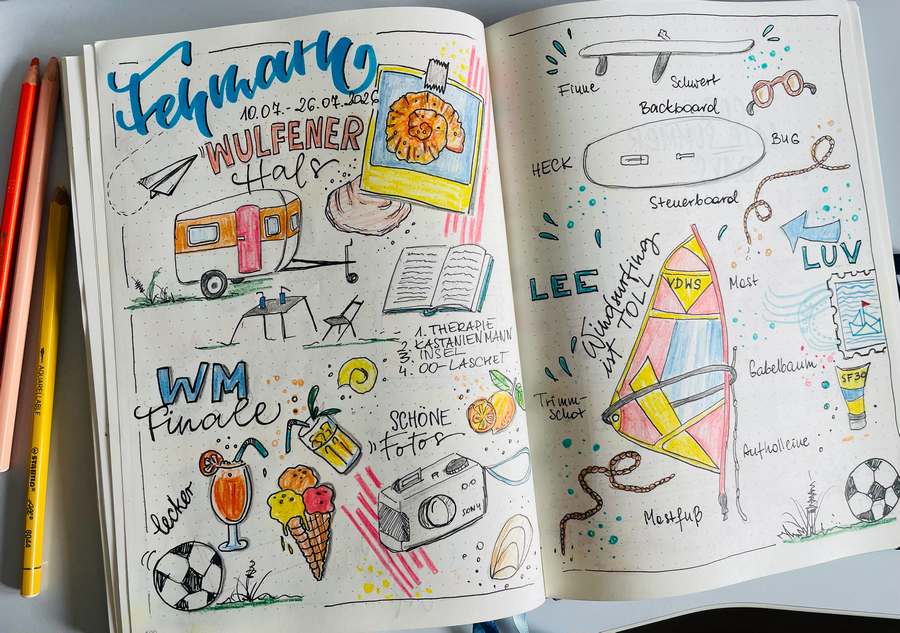
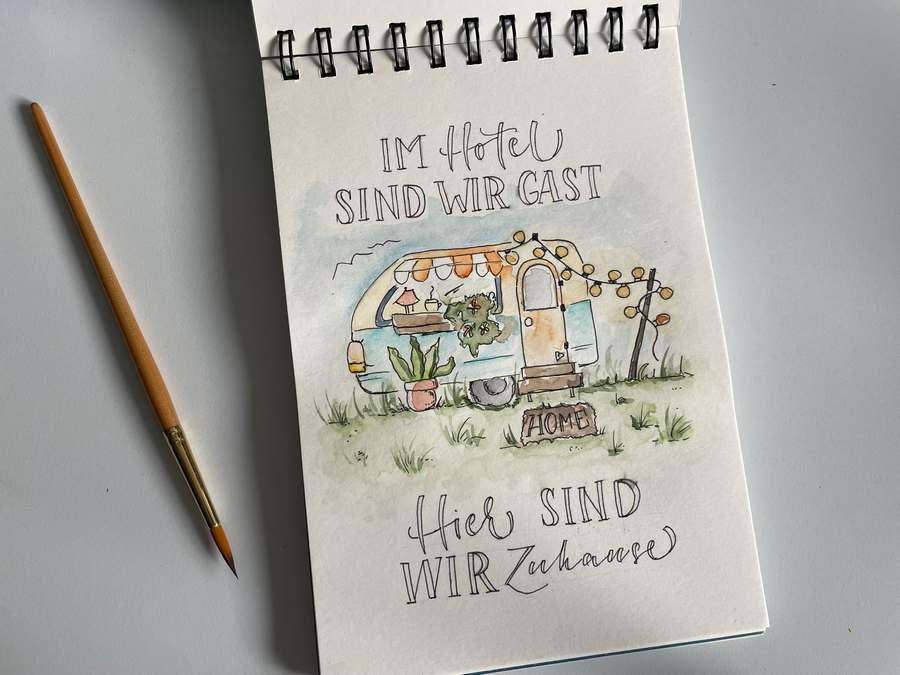
Niby nic nie wrzcuałam na IG, ale przeglądając swoje wakacyjne zdjęcia widzę, że kilka tych letteringów jednak było- czy to zwykłym ołówkiem, czy w Procreate. Ot, to moje ogormne hobby, które mnie bardzo relaksuje i tworzę sobie zwsze gdy nadejdzie mnie ochota.
W te wakacje przeczytałam i przesłucham (ja na mnie) sporą liczbę książek. Wszystkie były po niemiecku, więc niestety nic nie będę polecać 😀 Uwielbiam thrillery i kryminały, ale na liście znalazły się też komedia i romansidło- też fajne i wciągające. Musiałam się trochę zmusić do czytania i siedzieć na tyłku, a nie ciągle gdzieś latać- ja latem nie potrafię usiedzieć na miejscu- zwłaszcza, gdy jest piękna pogoda. W tym roku opaliłam się na maxa. W moim całym życiu nie byłam jeszcze NIGDY tak opalona. Praktycznie od końca maja mieliśmy pogodę i popołudnia spędzałam na plaży lub w ogrodzie. Kocham słońce i lato tutaj nad Bałtykiem….
Zdjęcia z tegorocznego lata- Bałtyk wyspa Fehmarn oraz u nas w Kiel-Schilksee 🙂 Ładnie u nas, prawda?
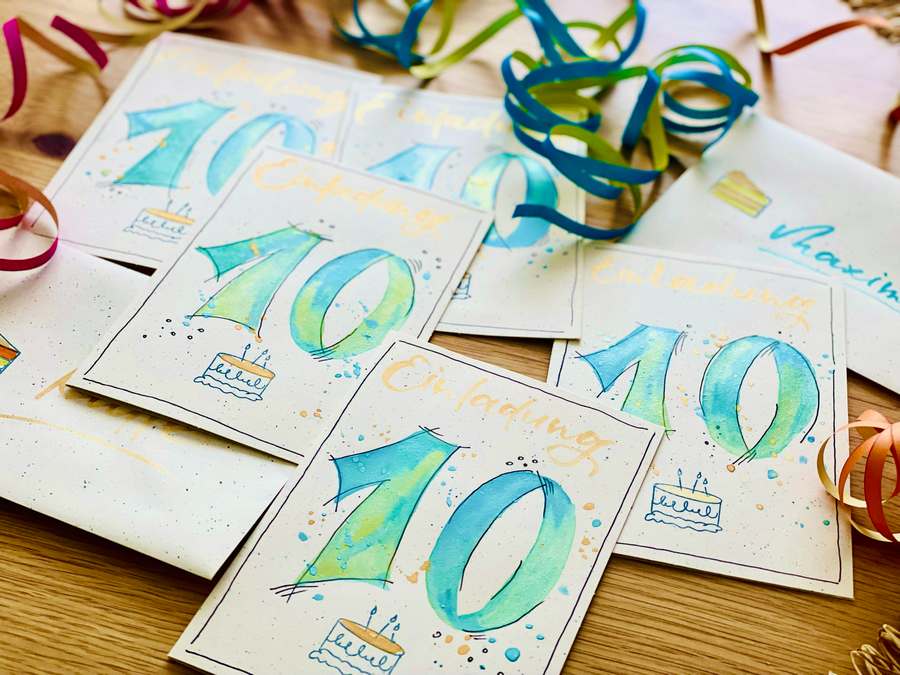
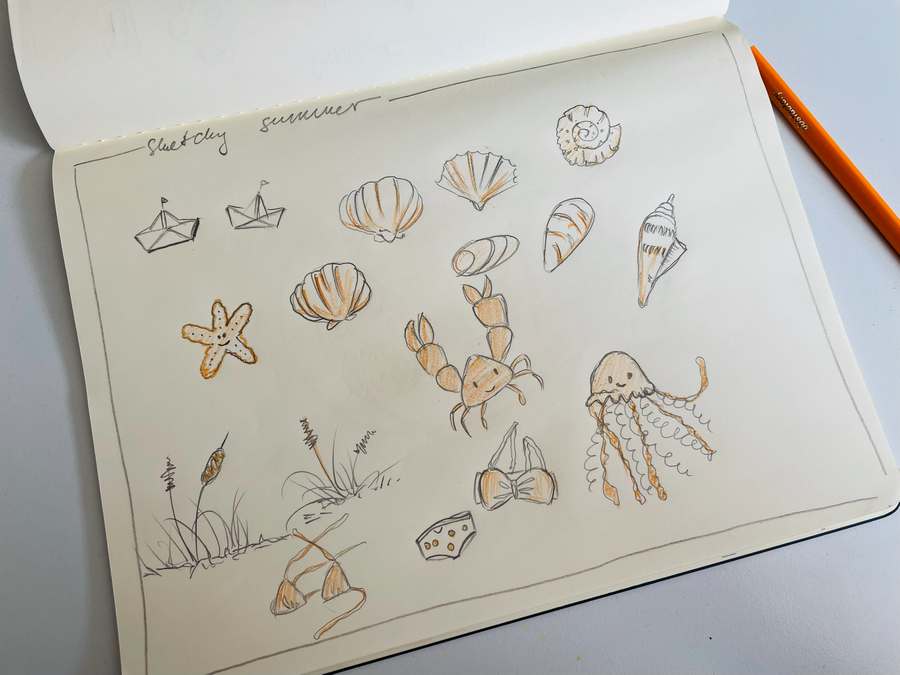
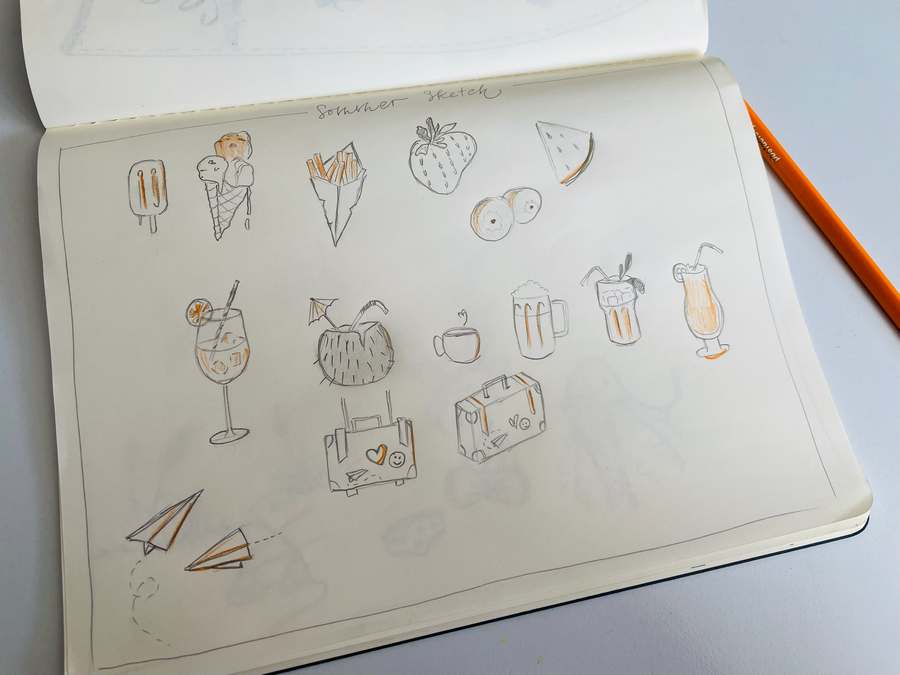
Moja ulubiona technika w letteringu? Ołówek. Projekty powstają dla mnie, nie na zamówienie i tutaj ołówek sprawdza się najlepiej. A każdą niedoskonałość można wymazać i poprawić. Takie rysowanie zajmuje dosłownie 20 minut i sprawia ogromną radość.
Korzystam też z kredek, ale rzeczywiscie kolory pojawiją się u mnie coraz rzadziej. Opanowałam obsługę brush penów do perfekcji i po prostu mi się znudziło. Dlatego sięgam coraz częściej po inne narzędzia. Ale nie od razu Rzym zbudowano, to natuarlny proces. Brush lettering przyszedł do mnie jako pierwszy, a potem doszły inne kroje pisma, które z biegeiem czasu włączyłam do moich projektów.
W czasach AI coraz rzadziej można trafić na proste i autentyczne teksty ludzkie, niegenerowane przez maszyny. A tym bardziej zdjęcia, czy letteringi można dziś bez problemu wygenrować w dodwolnym AI-programie. Wśród tych sztucznych wytworów nie potrafię się odnależć. Wszystko na jedno kopyto, podobny styl. Tym bardziej doceniam moje wyuczone zdolności. Nigdy o sobie na myślałam – artystka. Ja nie mam talentu za grosz. Setki godzin ćwiczeń doprowadziły mnie do tego etapu. Wiem, że może być lepiej i ładniej i bardziej profesjonalnie. Ale ja na tym etapie powiedziałam sobie dość. I chyba udało mi się odkryć swój styl. Czy to letteringi, czy rysunki mają swój jednolity vibe. I tyle. Sprawia mi to radość, jedne prace są lepsze inne gorsze. Ale frajda podczas tworzenia jest niesamowita. Moja joga dla umysłu. Nawet gdy szukam celowo jakichś treści interntowych, coraz mniej ich. Czy lettering był tylko krótkim trendem, który właśnie przeminął? Na ten temat napisałam rok temu spory artykuł- zapraszam.
Obecnie dosyć rzadko sięgam po tablet i Procreate. Latem powstały zaledwie 3 prace. Sama nie wiem dlaczego. Chyba po prostu nie chciałam patrzeć na monitor tableta.
Wycofanie ze social media przyszło jakoś naturalnie. Tego wszystkiego było mi tam za dużo, za sztucznie, przerost formy nad treścią. No i wszędzie reklamy i AI. Oczywiście treści na moim IG, czy na facebooku będą się nadal pojawiać. Ja staram się wyłączać te wszystkie reklamy, twory AI, które mnie po prostu męczą. Poza tym życie toczy się poza monitorem komputera czy telefonu. To tylko social media. Chcę z nich czerpać wiedzę, a nie marnować czas.
Niestety jesień nadchodzi wielkimi krokami. Nie lubię jej. Ale postaram się ją dobrze sporzytkować i pomalutku zmieniam kolory w letteringach.
Mam nadzieję, że twoje lato było udane.